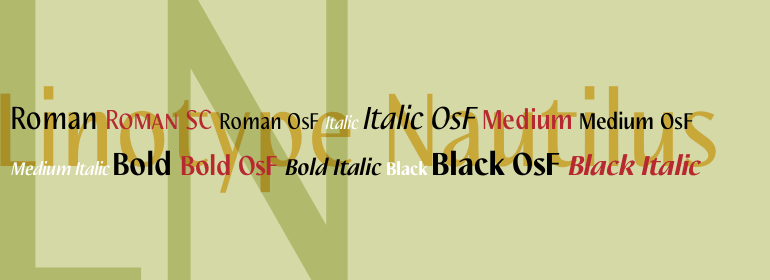
Linotype Nautilus™
Linotype Nautilus™,这款字体结构工整、笔画清晰,兼顾美观与易读性,适用于标题、正文、海报、包装、LOGO 等多种场景。字形优雅稳定,风格百搭耐看,适配日常排版与创意设计,让文字呈现更舒适、更具质感。Linotype Nautilus™一笔一画,皆是细节,以均衡的比例、流畅的线条打造舒适视觉体验,字形端正大气,风格简约现代。无论是商业设计、品牌宣传还是日常排版,都能轻松驾驭,让文字更有格调与力量。Linotype Nautilus™字体下载。
Hellmut G. Bomm first released his Linotype Nautilus typeface in 1999. Ten years later, he updated and expanded the design. Now users have two additional families at their disposal: Nautilus Text and Nautilus Monoline. Nautilus Text bears more similarities to the original Linotype Nautilus. The letters shows a high degree of contrast in their stroke modulation. Bomm's intention was to create a clear, highly legible face. While the even strokes of most sans serif types eventually tire the eyes in long texts, the marked stroke contrast of Nautilus Text lends the face its legibility. The characters were drawn with a broad tipped pen. Like serif typefaces, the forms of Nautilus Text display a variety of elements. Its characters are narrow, with relatively large spaces between them. This helps create an overall open appearance, and allows a large quantity of text to fit into a small space. Nautilus Monoline's letters share the same overall proportions as Nautilus Text's. But as their name implies, they are monolinear. Their strokes do not have the calligraphic modulation that Nautilus Text features. This allows them to set another sort of headline, making Nautilus Monoline a refreshing display type choice to pair with body text set in Nautilus Text.